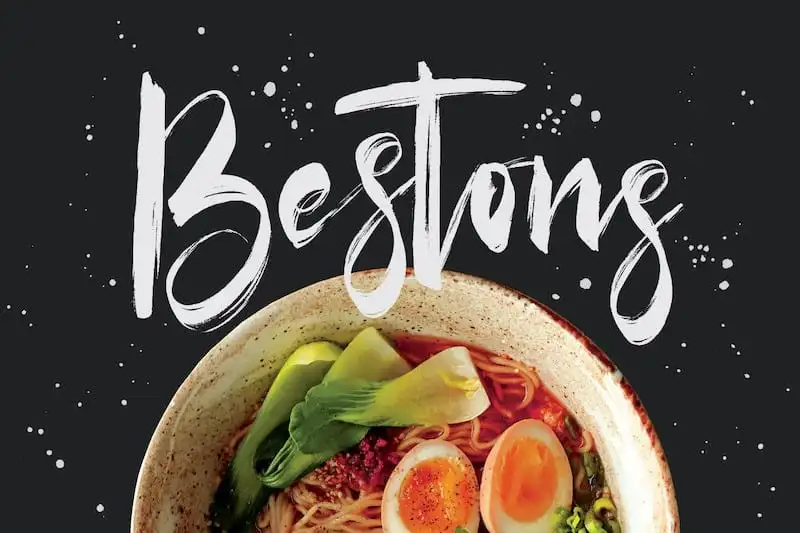
Bestons Brush Font – Download Grátis
A “Bestons Brush Font” é uma fonte elegante e fluida criada a partir do uso de uma caneta-pen. Esta fonte é ideal para quem busca dar um toque autêntico a seus designs digitais, adicionando uma sensação única e encantadora ao seu trabalho. Desenvolvida pelo designer Maulana Creative, essa tipografia fluída se destaca especialmente nas aplicações como assinaturas, selos de papelão, logotipos, citações em publicações, capas de livros ou revistas, cabeçalhos de sites e anúncios, roupas ou embalagens. Com a “Bestons Brush Font”, você pode transformar qualquer projeto digital em uma criação verdadeiramente personalizada e cheia de charme, incorporando um toque autêntico da arte da caneta-pen ao design.